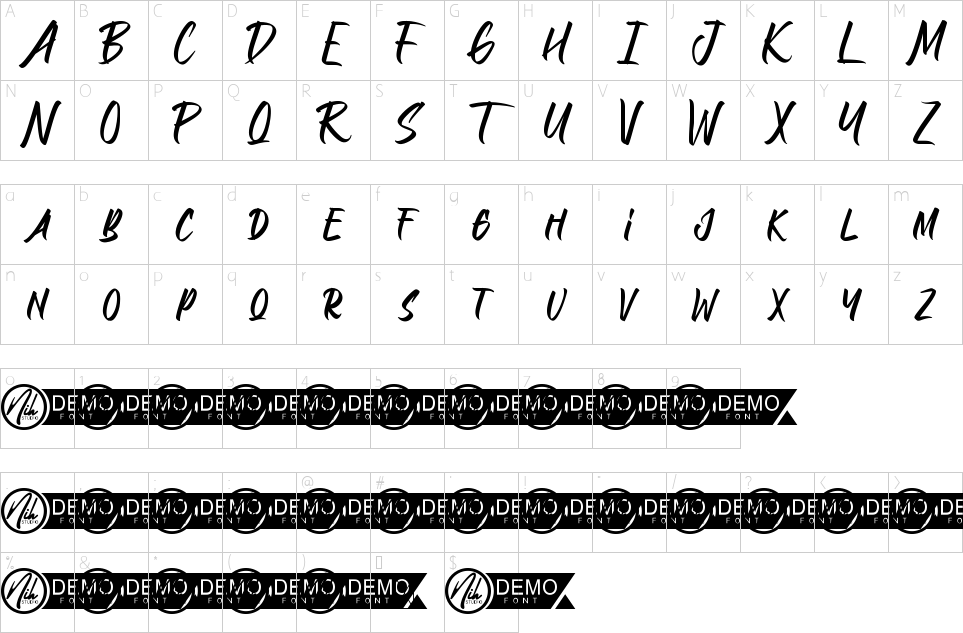
Descubra Thebig Font, uma elegante e versátil fonte para uso personalizado no seu projeto digital. Desenvolvida pela nihstudio, esta fonte é perfeita para quem busca um estilo que combine sofisticação com simplicidade. Com o design minimalista e alegre do Thebig Font, você pode criar gráficos e layouts modernos e chamativos sem sacrificar qualidade ou estilismo. Baixe agora para experimentar suas múltiplas utilizações em projetos digitais, desde websites até designs de aplicativos móveis. Com um design minimalista, a Thebig Font oferece uma experiência visual fluida e funcional, tornando-a um recurso indispensável para todos os profissionais de design. Desfrute desta fonte gratuita e descubra por si mesmo seu potencial criativo.